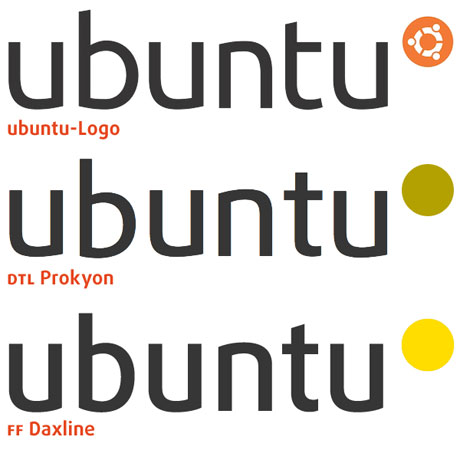
Ubuntu ist eine Linux-Distribution, also eine Zusammenstellung des Linux-Kernels mit diverser Software, um hieraus ein Betriebssystem zu bilden. Der Name bedeutet auf Zulu »Menschlichkeit« und bezeichnet eine afrikanische Philosophie, die den Markenkern von Ubuntu widerspiegelt: ein einfach zu installierendes und leicht zu bedienendes Betriebssystem mit aufeinander abgestimmter Software.
Die kommende Version 10.04 des beliebten Linux-Betriebssystems mit Codenamen »Lucid Lynx« nimmt Abschied vom traditionellen Human-Theme in Erdtönen. An seine Stelle tritt das Light-Theme, mit dem auch gleichzeitig das Ubuntu-Logo einen neuen Anstrich bekommt (Abb unten). Mehr zum neuen Theme und dem Redesign auf der Ubuntu-Wikiseite ›Brand‹. Verantwortlich für die Ausarbeitung der neuen Markenwerte ist ein kleines Team um Mark Shuttleworth, das seit 2009 kontinuierlich am Redesign der Marke arbeitet.
Man hätte die neue marke auch gleich in „unbuntu“ umtaufen können…
@spiekermann: LOL, genau das trifft’s. Ich finde es echt schade, dass dieser Menschenkreis nur noch eine Farbe hat. Das alte Logo hatte so schön simpel die Gemeinschaft der Völker visualisiert, und damit auch das Open-Source-Prinzip. Dazu noch dieser sympathische Schriftzug.
Die neue Typo passt vielleicht zum ›leichten‹ Stil, sieht aber nicht sehr einladend aus. Eine totale Kehrtwende: Vom freundlichen Open-Source zu strenger, schlichter Software. Gefällt mir nicht.
Ist das ein Schatten, eine Kontur oder einfach nur Schlampigkeit bei der mausgrauen Schrift? Flimmert übel. Ich vermisse die runde Fröhlichkeit und die klaren Farben der alten Version.
Dafür geht es auf der Kühlschranke Seite aber wieder ganz schön bunt zu, dort werden einzelne Logos zu Unterkategorien gezeigt und die Umsetzung finde ich dort mehr als misslungen.
„zubuntu“
Was sagt ihr denn zum Font? Ich bin immer wieder angetan, wenn ihr Fonts analysiert.
marketingleute, die mit irgendwelchen an den haaren herbeigezogenen zusammenhängen zur »afrikanischen philosophie« ankommen gehören sofort mit bösestem voodoo-zauber belegt. auf das sie auch weiterhin und bis in alle ewigkeit gezwungen sind, bildmarken zu produzieren, die man wegen der zu kleinen abstände nicht verkleinern kann.
Zum Font sage ich: Es war mal eine FF Dax (genauer FF Daxline), und alles was daran gemacht wurde, hat es nicht besser gemacht.
Auf typophile.com ist auch eine Diskussion im Gange über die Schrift. Da wird behauptet es sei DTL Prokyon. Aber was auch immer.
Bei der Dax muß ich immer und ausschließlich an UPS denken…
Wozu noch das logo oben rechts. Ist doch so völlig sinnlos.
Gleich besser ganz weggelassen.
charakterlos, schlecht umgesetzt und überhaupt noch weniger emotionen als das alte logo. gerade der gag mit den wechselnden farben (köpfen, punkten) geht nun völlig unter. kurz: http://www.youtube.com/watch?v=IyCCuKJge-E
‘Ubuntu’ (Logo)Type: ‘The work has been commissioned from world-renowned fontographers Dalton Maag …’
Hier erzählt Mark Shuttleworth über das Ubuntu Redesign und die neue Schrift, gestaltet von DaltonMaag (steht weiter unten im Artikel). In der Diskussion bei typophile hat octoploid das Logo mit der Prokyon verglichen. Hier der Vergleich mit der Dax (DaxlinePro Regular).
Bei typophile hat sich eben noch David Marshall / DaltonMaag persönlich zu Wort gemeldet: „…And no, of course it’s not plagiarized – like all of our custom designs it was drawn from scratch with no reference to any existing font…“
Das Logo find ich o.k., nicht schlecht.
Viel interessanter find ich allerdings das UI.
Ein Riesenschritt für Ubuntu und sehr gelungen auf den ersten Blick :)
Dalton Maag schreibt auf Typophile: »While there are superficial and coincidental similarities between the handful of characters you’ve seen, the rhythm, proportions, and details are completely different between the two fonts.«
Tatsächlich finden sich im ubunto-Logo eigentlich »nur« 3 wirklich unterschiedliche Buchstabenformen (u=n) … die restlichen Zeichen sollen noch in Arbeit sein. Es besteht also noch Hoffnung, dass die Schriftart am Ende ausreichend von DTL Prokyon und FF Daxline abweicht. Wir werden das beobachten.
Warum müssen eigentlich Prokyon und Daxline nicht voneinander abweichen? Sind die vom selben Entwerfer?
Irgendwie gehts immer nur um die Ubuntu-Schrift, ob die ein Plagiat ist.
Abgesehen davon frage ich mich schon, worin das Schützenswerte bestehen soll, daß es ja keiner nachmachen darf. Der Winkel, in dem der Bogen des “u” auf den Abstrich trifft? Der Verzicht auf den spur?
Die Übernahme eines anderen Fonts (also der .otf-Datei) und simples Verschieben einiger Kontrollpunkte steht ja nun offenbar nicht im Raum.
@Herrn Siebert: ‘b’, ‘n’, ‘t’ und ‘u’ ergeben für mich 4 Buchstaben. Moment, ich zähl nochmal nach … Nö, vier; obwohl ich eingestehen muss, dass ‘n’ und ‘u’ von ihrer Form her nach bei einander stehen.
Aus Sicht eines Schriftentwerfers kann man bei dieser Klasse konstruierter Sans-Serif-Schriften das n und das u einfach mal als identisch bezeichnen.